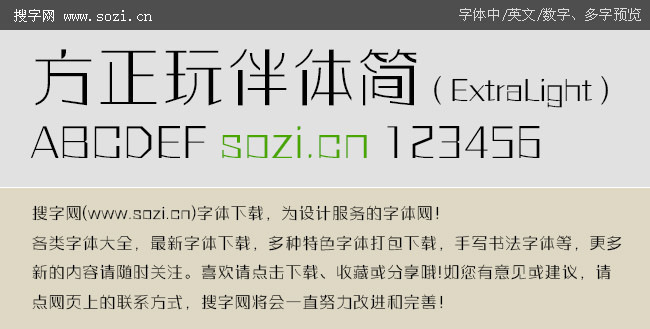
方正玩伴體簡(jiǎn)ExtraLight
搜字網(wǎng)提供一款方正玩伴體簡(jiǎn)ExtraLight中文字體下載,方正玩伴體風(fēng)格獨(dú)特,創(chuàng)意很新鮮,它的筆劃都有些反叛行為的構(gòu)思,有一種與眾不同的感受,它含8款粗細(xì),適合年青人品牌,舞蹈用品,酒店,旅行社和品牌食品的廣告宣傳和包裝設(shè)計(jì)。